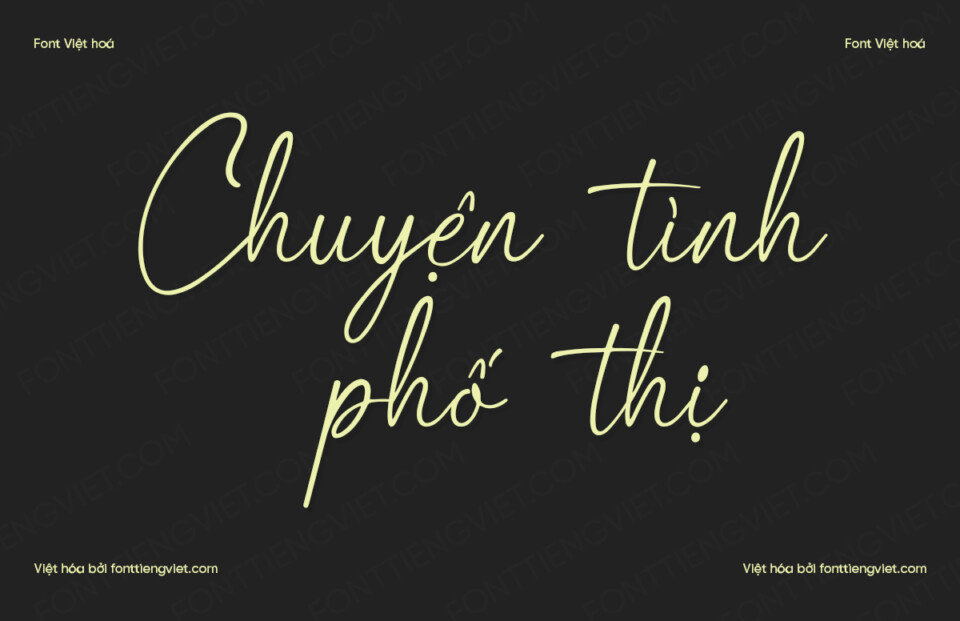
Trong thế giới thiết kế hiện đại, việc tìm kiếm một bộ Font Chữ vừa mang nét sang trọng vừa đảm bảo tính đọc hiểu cao là điều rất quan trọng. Font Việt hóa 1FTV VIP Palisade nổi lên như một sự lựa chọn hàng đầu cho các thầy cô giáo và học sinh khi thực hiện các bài thuyết trình hay thiết kế tài liệu học tập. Bộ font này không chỉ mang đến sự mới mẻ về mặt thị giác mà còn giúp thông điệp truyền tải trở nên chuyên nghiệp và tinh tế hơn bao giờ hết.
Đặc điểm nổi bật của Font Việt hóa 1FTV VIP Palisade
Thiết kế thanh lịch và hiện đại
Bộ font này sở hữu những đường nét mảnh mai nhưng vô cùng dứt khoát, tạo nên một cấu trúc cân đối và hài hòa. Font Việt hóa 1FTV VIP Palisade đặc biệt phù hợp cho các tiêu đề lớn, bìa sách giáo khoa hoặc các bảng tin nhà trường. Sự kết hợp giữa nét cổ điển và hơi thở đương đại giúp bộ chữ này dễ dàng thu hút sự chú ý của người xem ngay từ cái nhìn đầu tiên.
Tối ưu hóa cho tiếng Việt
Điểm mạnh nhất của phiên bản này chính là việc xử lý dấu tiếng Việt cực kỳ mượt mà. Các ký tự dấu được thiết kế tỉ mỉ, không bị đè hay lệch so với chữ cái chính, đảm bảo văn bản luôn mạch lạc và dễ đọc trên cả thiết bị điện tử lẫn bản in. Đây là yếu tố sống còn giúp các bạn học sinh tạo ra những sản phẩm sáng tạo đạt chuẩn thẩm mỹ cao.
Sử dụng trong giảng dạy và học tập
Các thầy cô có thể dùng font chữ này để làm slide bài giảng thêm sinh động, giúp học sinh tập trung hơn vào nội dung bài học. Với phong cách chuyên nghiệp, nó cũng rất phù hợp cho các chứng chỉ, bằng khen hoặc thiệp mời sự kiện tại trường học. Để cài đặt, bạn chỉ cần tải tệp về, nhấn chuột phải và chọn cài đặt để bắt đầu sáng tạo ngay lập tức.